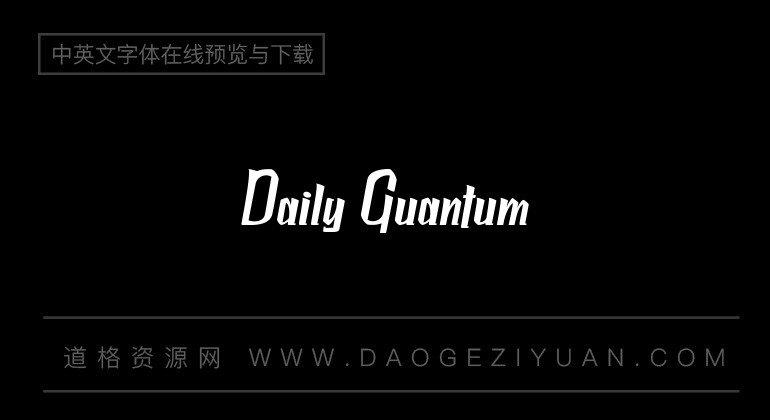
Daily Quantum 是一款多功能的现代技术字体,可以用于多种设计项目,如标题、标签、按钮、标语等。它的设计风格有着明显的量子特征,具有清晰的轮廓和流畅的笔画,拥有强大的表现力,为您的设计提供强大的支持。它的字体结构清晰,易于阅读,可以满足不同的设计需求,是一款全面的技术字体。内容介绍
Daily Quantum是一款非常不错的手写艺术字体,具有很好的视觉感,适合于文化类的宣传设计、商业类品牌的广告和产品包装设计以及个性化文字排版等较多场景。